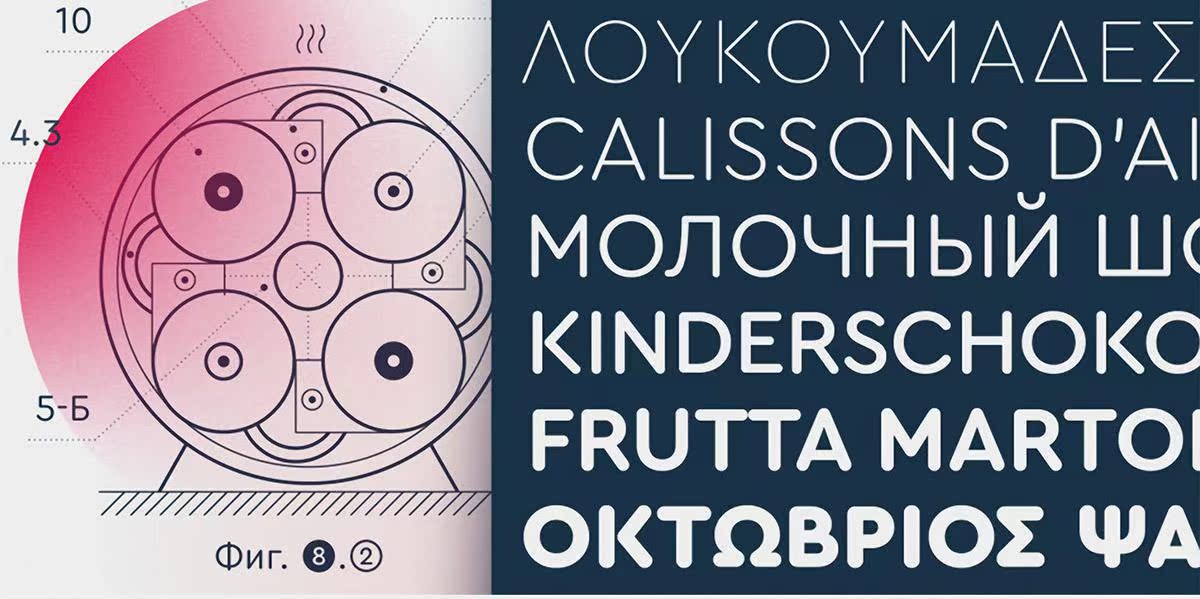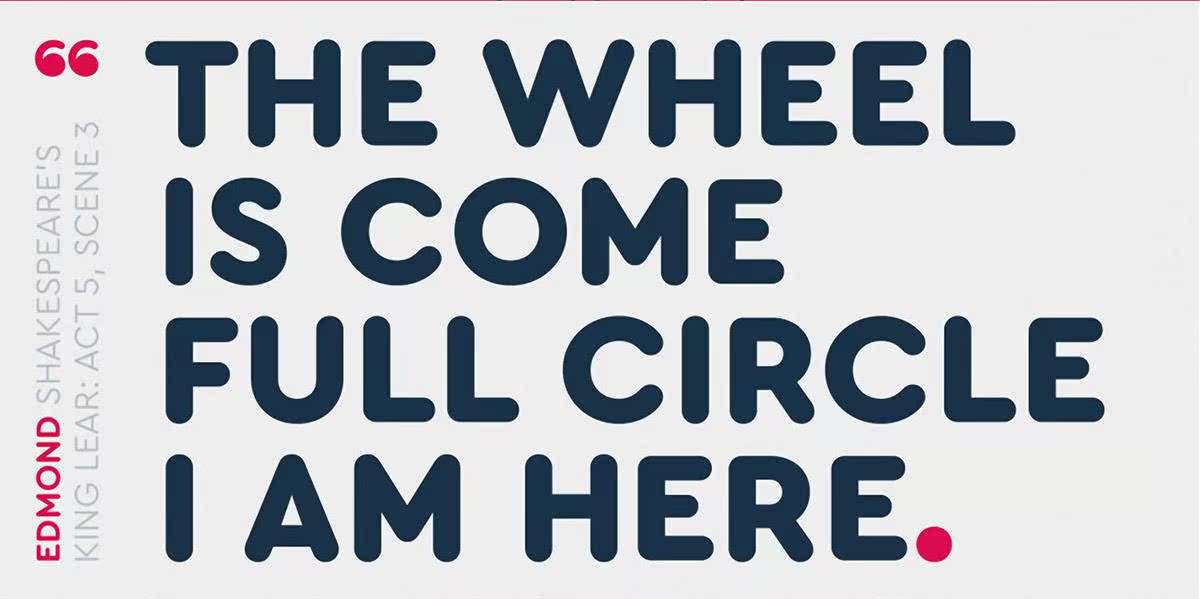
CeraloundProfreedeshisher!这种字体代表着你对拉丁语、西里尔语和希腊语的热爱。这种数字字体结合了强大的力量,为西里尔语和希腊语的国际交流提供了一个可靠的独立公司。对于长编辑文本来说,规则字体已经被完美地覆盖了。CeraloundPro的ssixweights,thintoblack,允许全方位的表达和显示排版。其中,轻量级具有所有技术图纸的清洁度和精度,其重量级可重复使用,且柔软:适用于坚固的包装和包装项目。